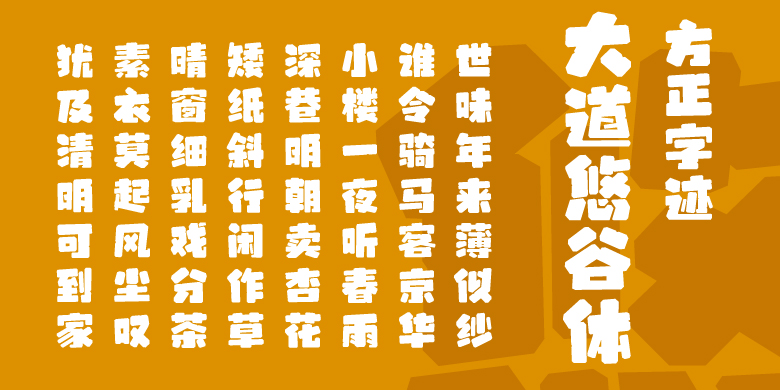
方正字迹-大道悠谷体
当原始人用燧石在洞穴石壁上刻下第一组符号时,人类文明的密码就此封存于斑驳的刻痕中。本套字体设计以新石器时代的物质遗存为灵感原点,通过现代数字技术重构石器时代的视觉语言体系。从出土的石斧、石锛、石凿等工具以及石块型制中提取造型元素,将每一笔画都淬炼为可触碰的实体: 厚重的楔形笔画如同冰川纪遗留的砾石,表面保留着人工打制的原始肌理,边缘处刻意保留的"磕碰"痕迹,恰似古人类在岩壁上反复捶打留下的岁月印记。 文字结构模拟原始建筑的桦卯智慧,看似歪斜的笔画实则暗含力学平衡,正如半坡遗址中倾斜却不倒的地穴式房屋。 字体整体呈现出笨拙却温暖的审美特质:敦实的笔画结构传递着原始人对力量的崇拜,不规则的边缘处理消解了机械字体的冰冷感。当现代屏幕投射出这些带着原始体温的文字时,仿佛穿越时空的隧道,触摸到新石器时代人类第一次用符号记录世界的悸动。故此,本套文字取名“悠谷”,寓意悠远古老峡谷中“石语者” 在深邃的山谷里到底隐藏着什么呢?等着我们去发发现。在这些斑驳的"石纹"里也许在某个隐秘的角落,悠谷的居民正充满好奇的也在窥探着你的一举一动。